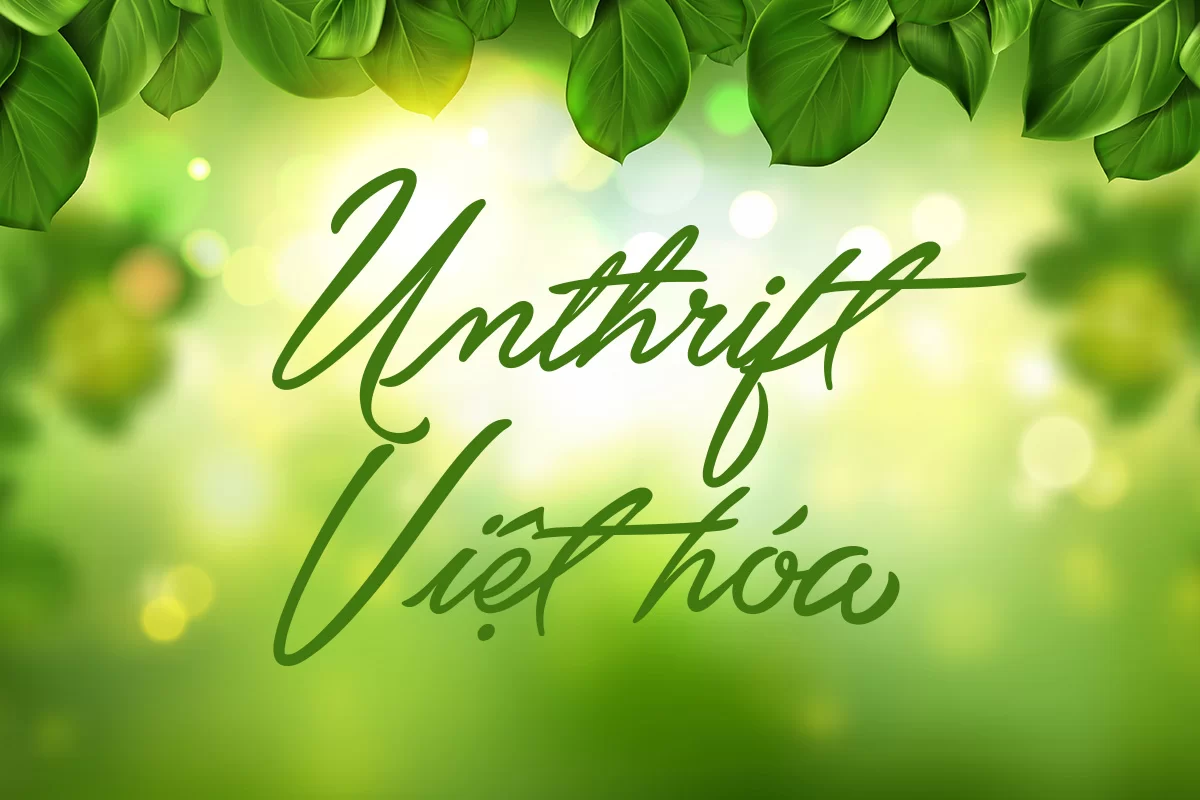
[Font Việt hóa] SVN-Unthrift - Font chữ uốn lượn khá đẹp
Unthrift, một phông chữ viết tay chất lượng cao, được Måns Grebäck tạo ra vào năm 2015. Phông chữ này có hai phiên bản: First và Second, mỗi phiên bản có một bộ chữ cái riêng biệt. Unthrift được xây dựng với những nét cọ lớn và sống động, lấy cảm hứng từ chữ viết tay những năm 90. Một số tính năng bao gồm bảng chữ cái thay thế, bảng chữ cái kết thúc, bảng chữ cái khởi tạo và bảng chữ cái swash. Ngoài ra còn có các bảng chữ cái thay thế theo ngữ cảnh và rất nhiều chữ ghép. Tất cả các tính năng này kết hợp lại tạo nên một nét chữ rất mượt mà và chân thực, cùng hàng ngàn khả năng tùy chỉnh.
Nhà thiết kế: Måns Grebäck
Nhà phát hành: Aring Typeface
Năm phát hành: 2015
Việt hóa: STYLEno.1 Fonts
Kiểu: Regular